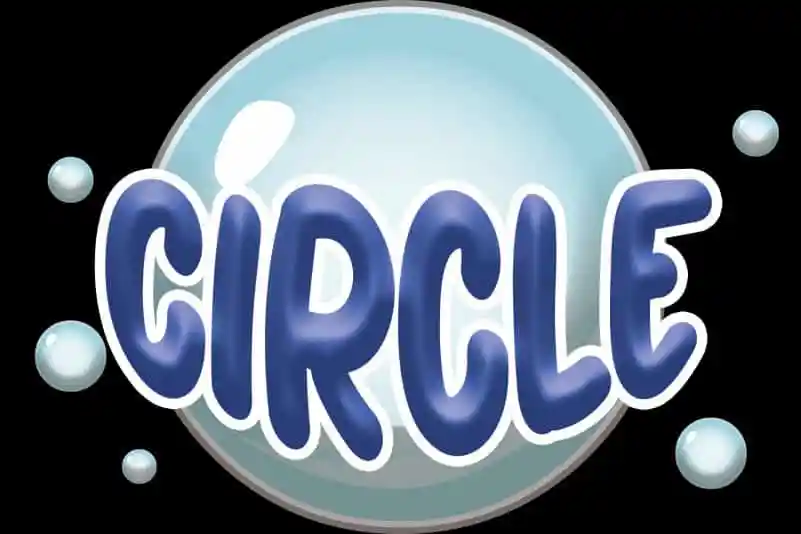
A fonte “Circle Display Font” é perfeitamente adequada para quem busca uma solução visual assertiva e limpa. Ela se destaca por sua elegância bold e simplicidade, sendo a escolha ideal para projetos que exigem um touch de personalização em design de arte ou criação de identidades visuais. Suave o suficiente para não perder sua essência, mas firme o bastante para destacar seu projeto. Ideal tanto para designers de arte quanto para criadores de identidade visual, esta fonte se encaixa perfeitamente nos designs que exigem uma paleta de cores sóbria e um design limpo. Seu uso em conjunção com trabalhos manuais ou arquitetônicos certamente transformará suas criações num verdadeiro destaque. Através da combinação desta fonte simplesmente bela, seus projetos atingirão o sucesso. Esta é uma maneira poderosa de expressar sua visão visual sem comprometer a simplicidade e o equilíbrio que tanto valorizamos em nossa era digital.